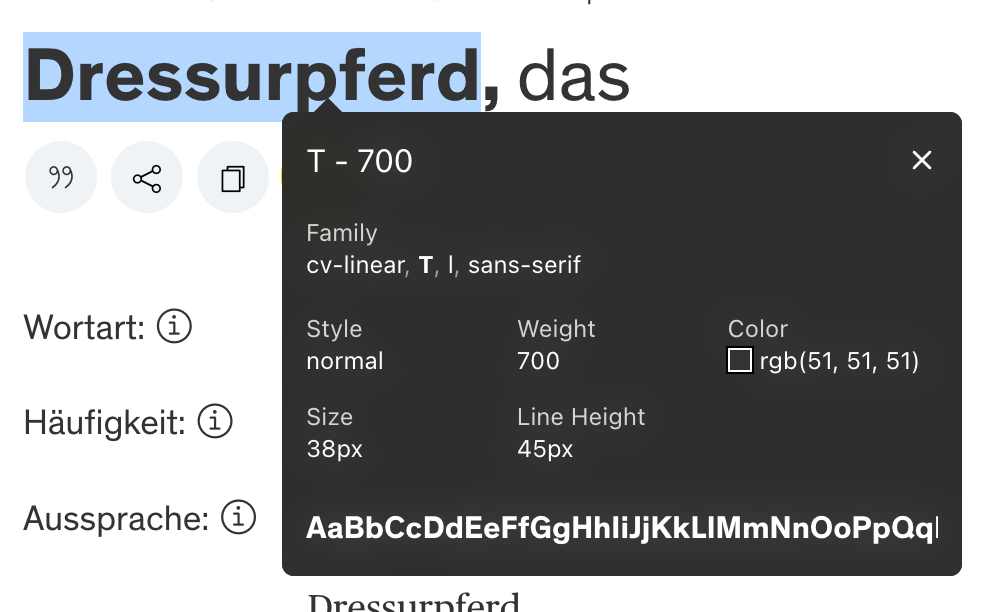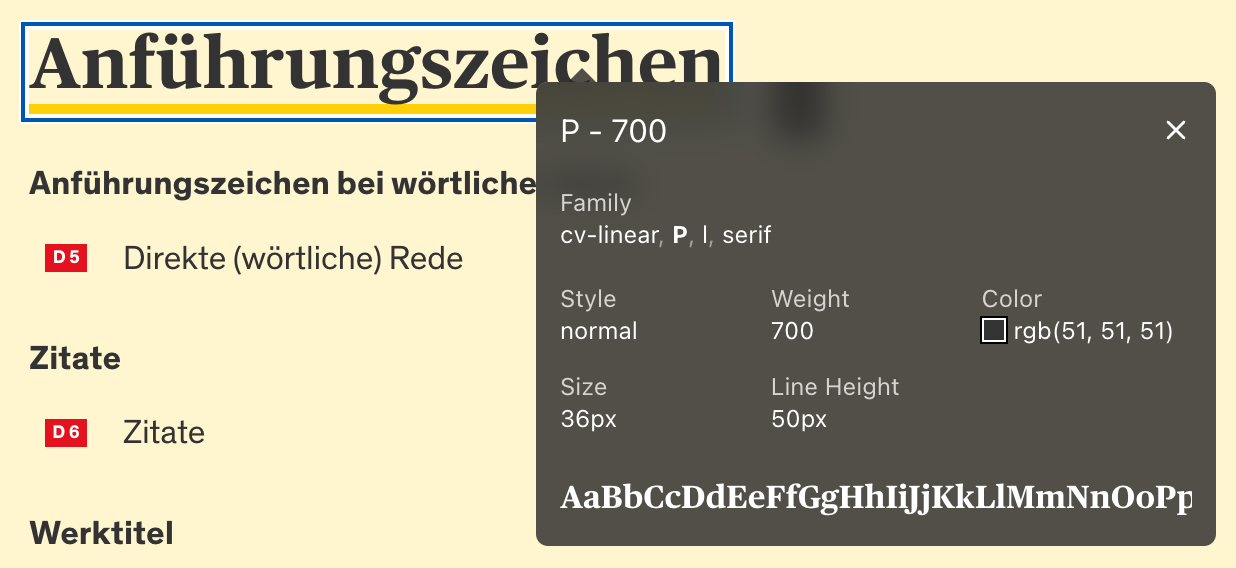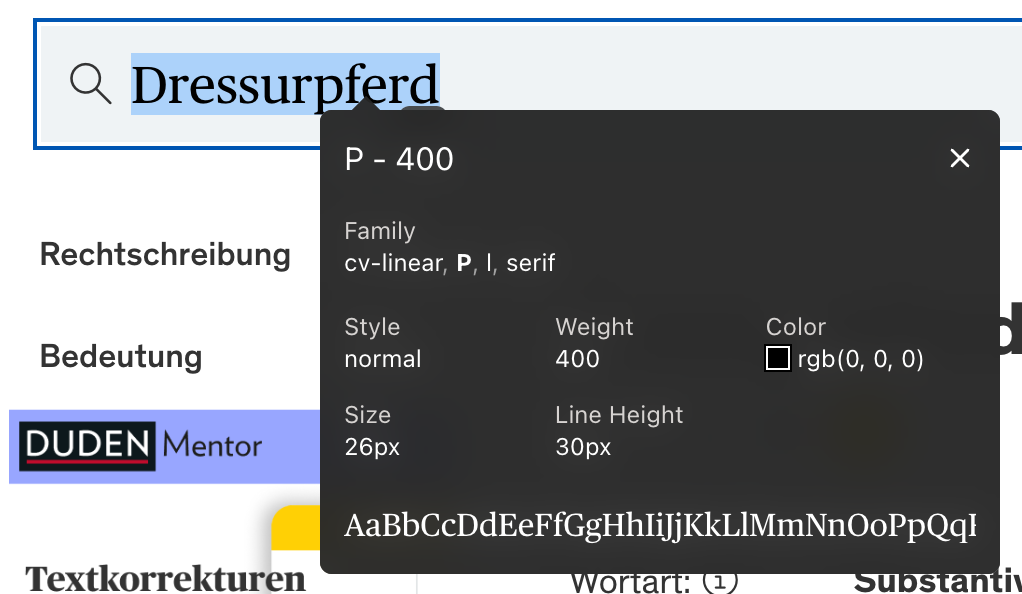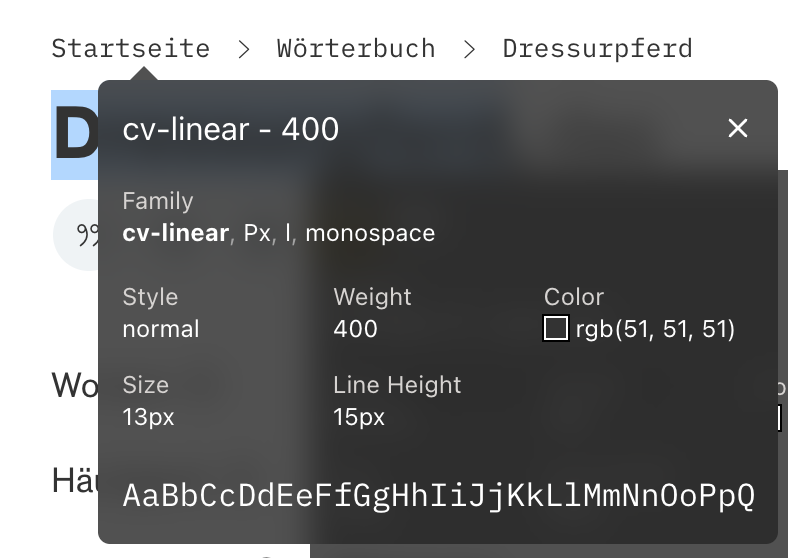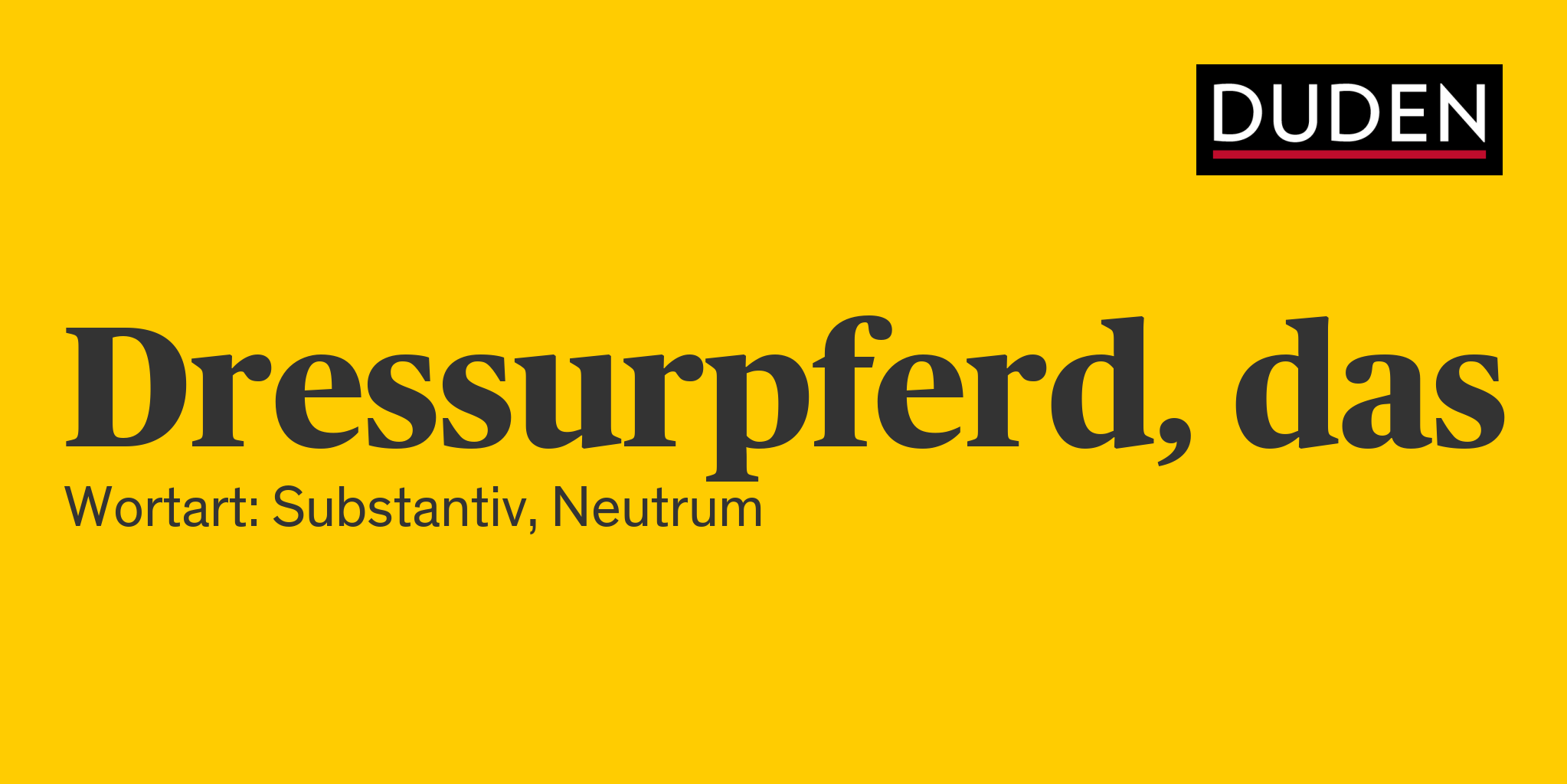
Welche Schrift benutzt der Duden?
Eine kurze, möglicherweise rare Frage: welche zwei Schriften werde für den Satz des Dudens verwendet werden?
Und welche Fonts werden bei den Suchergebnissen benutzt? Siehe Ergebnisbild aus Google. Unten („Wortart”) ist die Akzidenz-Grotesk, aber die obere ist nicht die Kepler. Wer kann mir bitte diesen Font identifizieren?
»cv-linear« klingt nach einer für den Cornelsen Verlag (CV) modifizierten oder kompilierten Hausschrift. Ansonsten wird das stimmen, mit der Theinhardt (T) und der Publico (P), die kamen ab 2017 zum Einsatz (nebst der Verlag von Hoefler & Co. im Logo, steht jedenfalls so in einem Artikel aus der Page von 2017, diese Ergänzungen wie Duden Mentor dürften dann auch die Verlag sein).
PS: Kepler und Frutiger für den Innenteil (ab ca. 2000) hat Iris Farnschläder, die den Innenteil damals überarbeitet hat, verantwortet, und Frutiger und Kepler wurden dann auch für die zeitgleiche Überarbeitung der Umschläge der Kernbände und das Logo eingesetzt (im Logo leicht modifiziert)